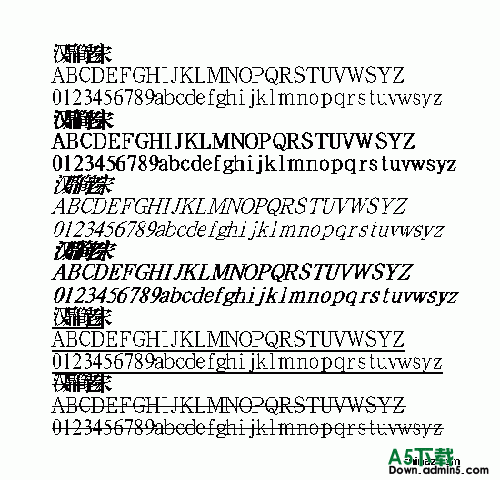
漢鼎簡(jiǎn)老宋字體是一款用于美工設(shè)計(jì)方面的字體,適合學(xué)習(xí)美工作業(yè)的朋友們使用,它雖然表現(xiàn)的形式比較特殊,但是在有些環(huán)境下還是能夠展現(xiàn)出完美的特色的,有需要的朋友可別錯(cuò)過了,綠色資源網(wǎng)提供最新中文字體和英文字體免費(fèi)下載。